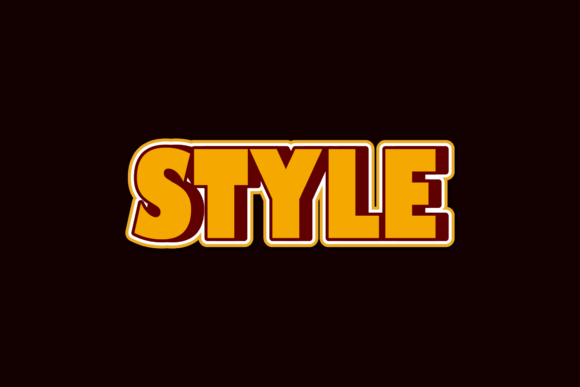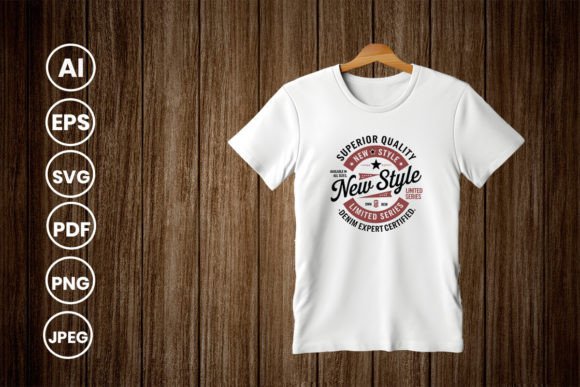
Typhography Style Graphic Crafts
การค้นหาองค์ประกอบการออกแบบที่เหมาะสมอาจเป็นเรื่องท้าทาย แต่ Typhography Style Graphic Crafts นำเสนอคอลเลกชันที่โดดเด่นซึ่งช่วยยกระดับงานของคุณได้ทันที
ไม่ว่าคุณจะสร้างผลิตภัณฑ์ POD (Print on Demand) คำเชิญงานแต่งงาน หรือกราฟิกโซเชียลมีเดีย Typhography Style Graphic Crafts ก็เหมาะสมอย่างยิ่ง